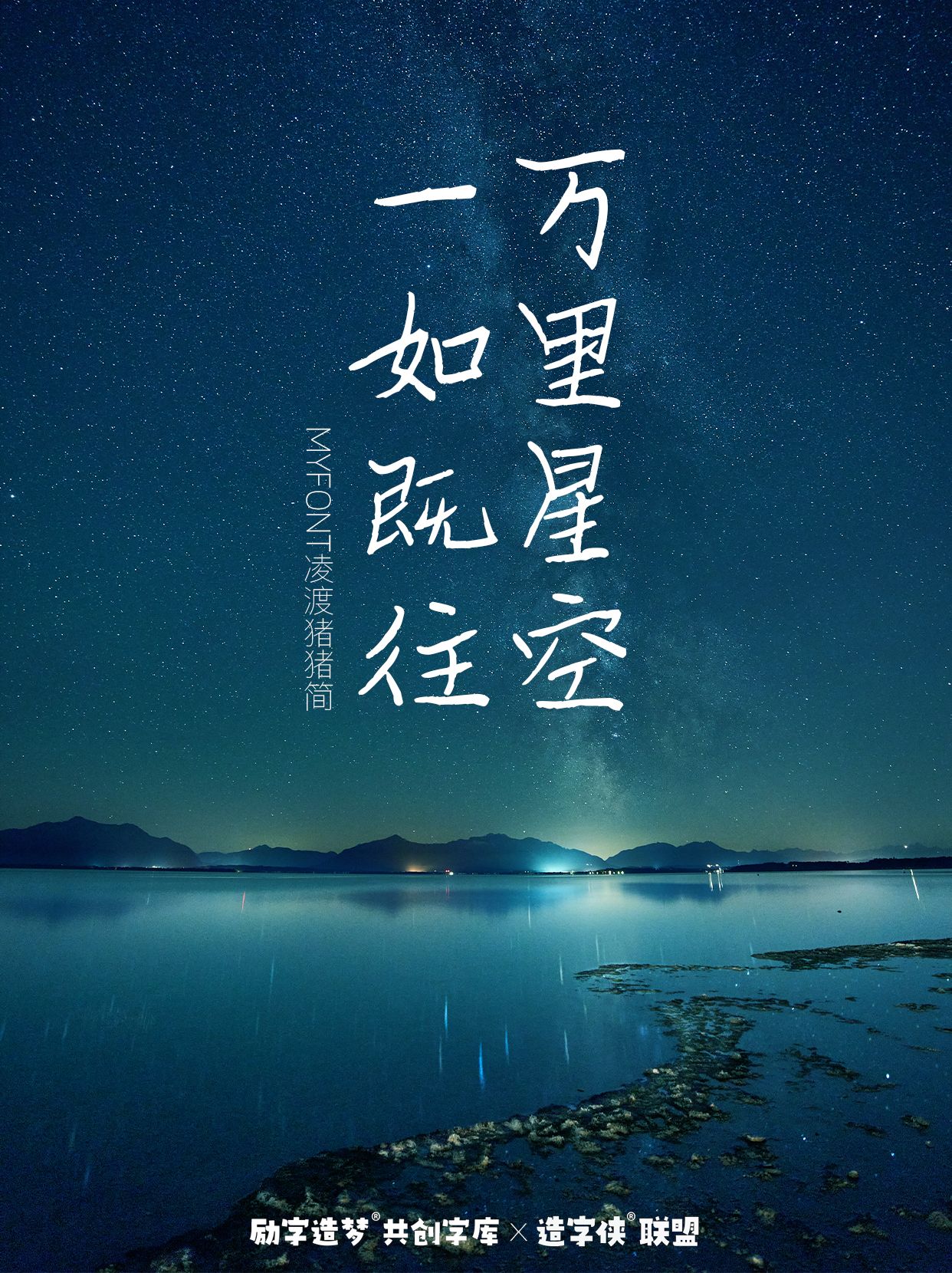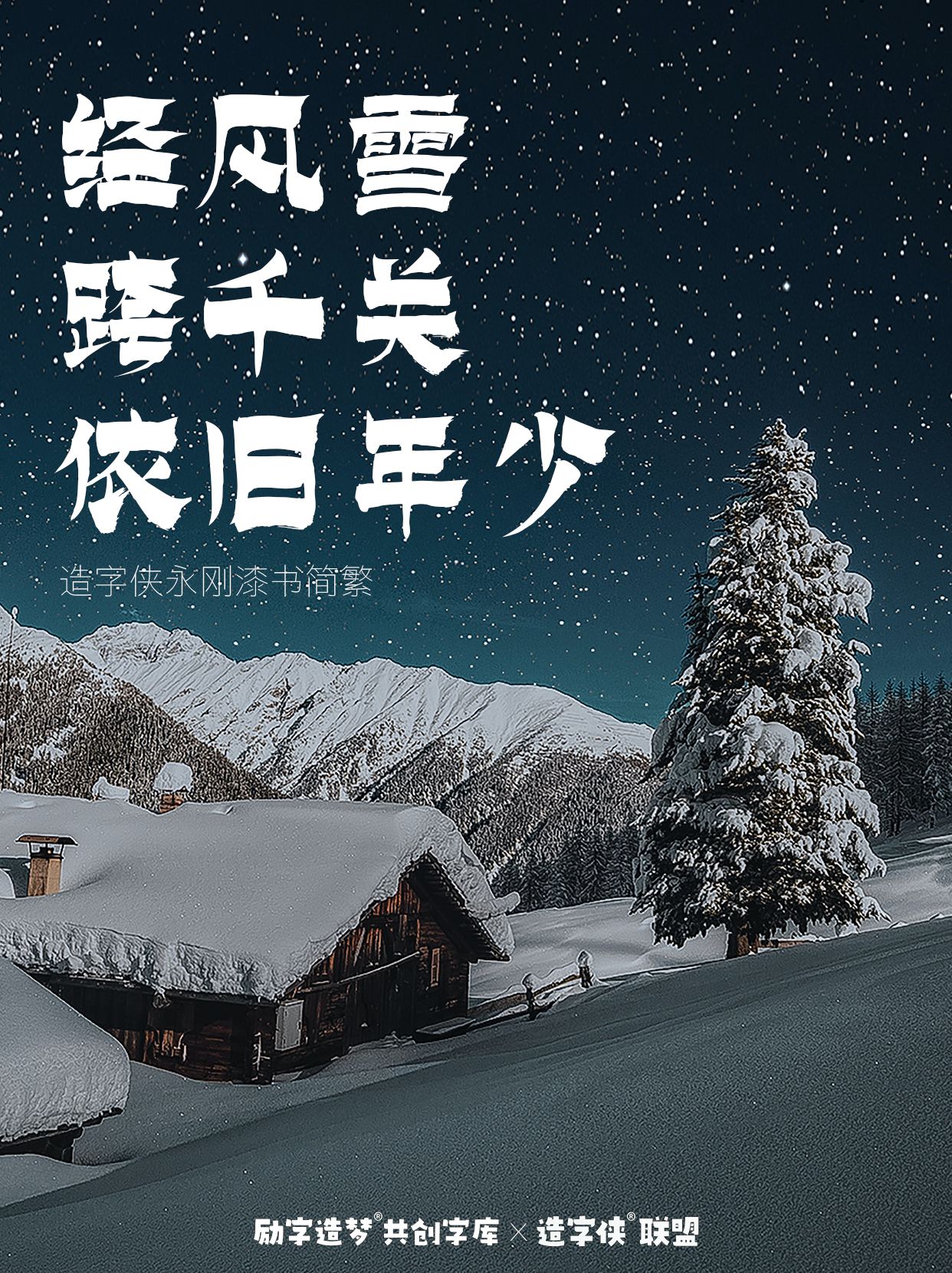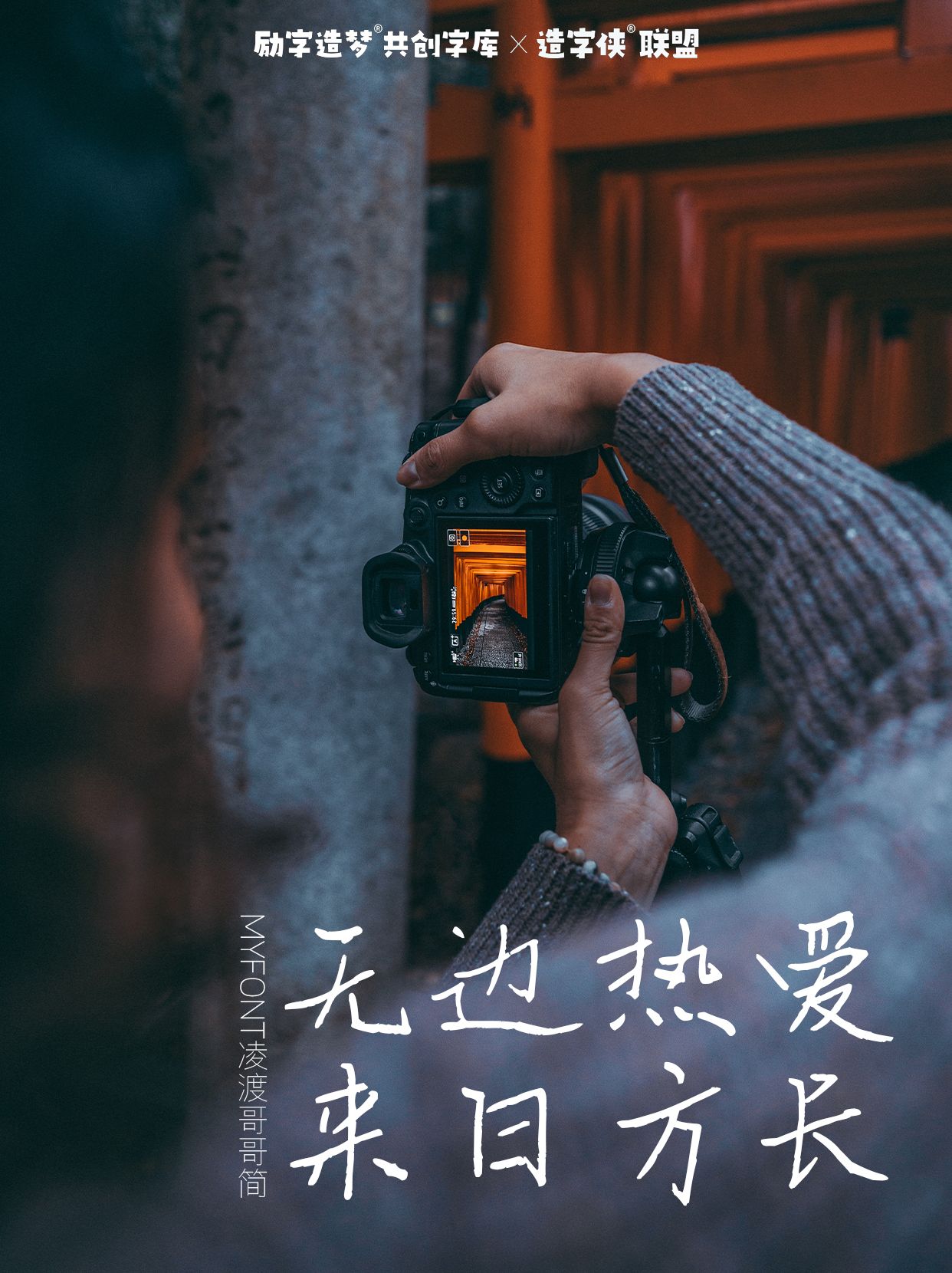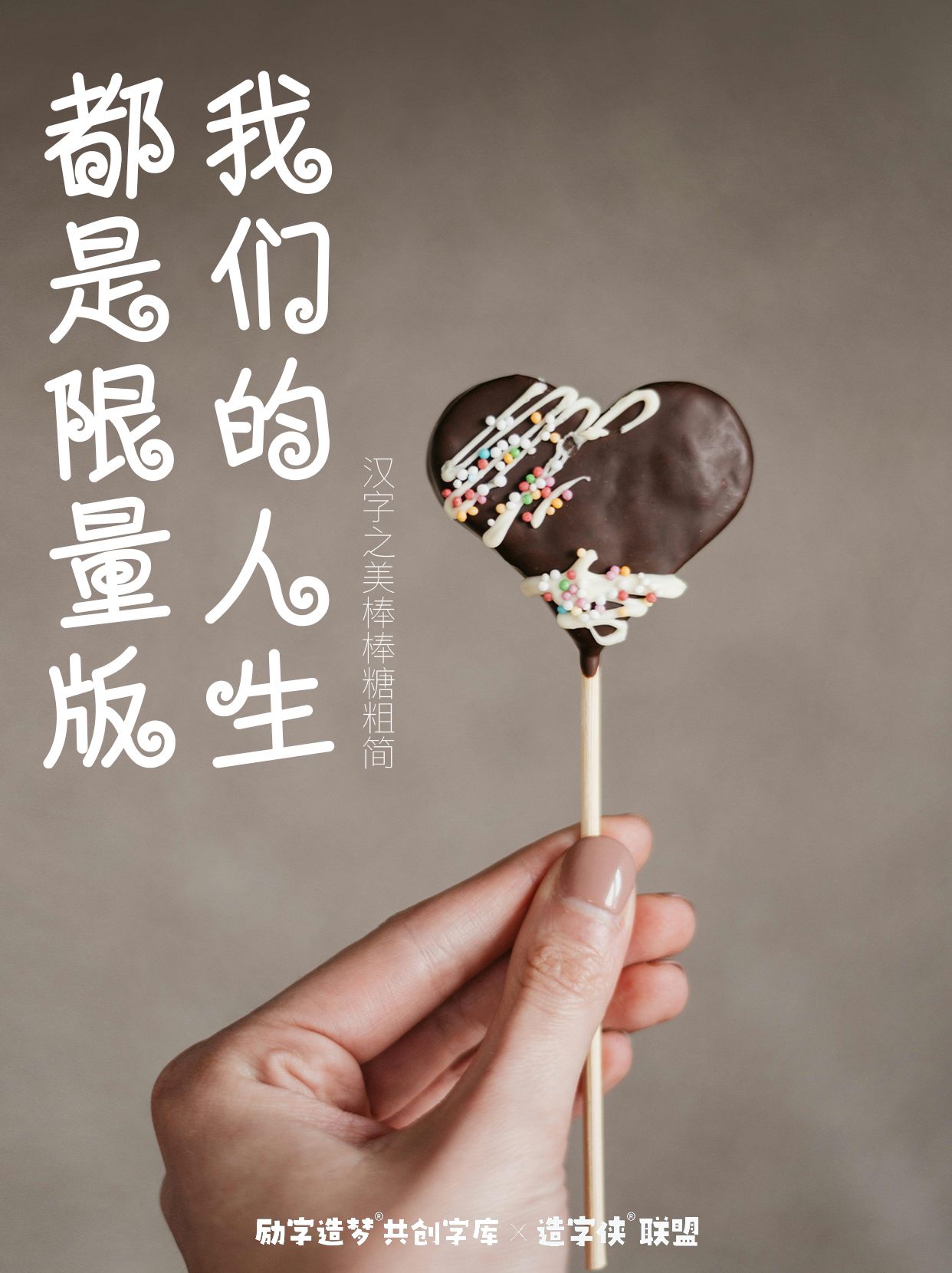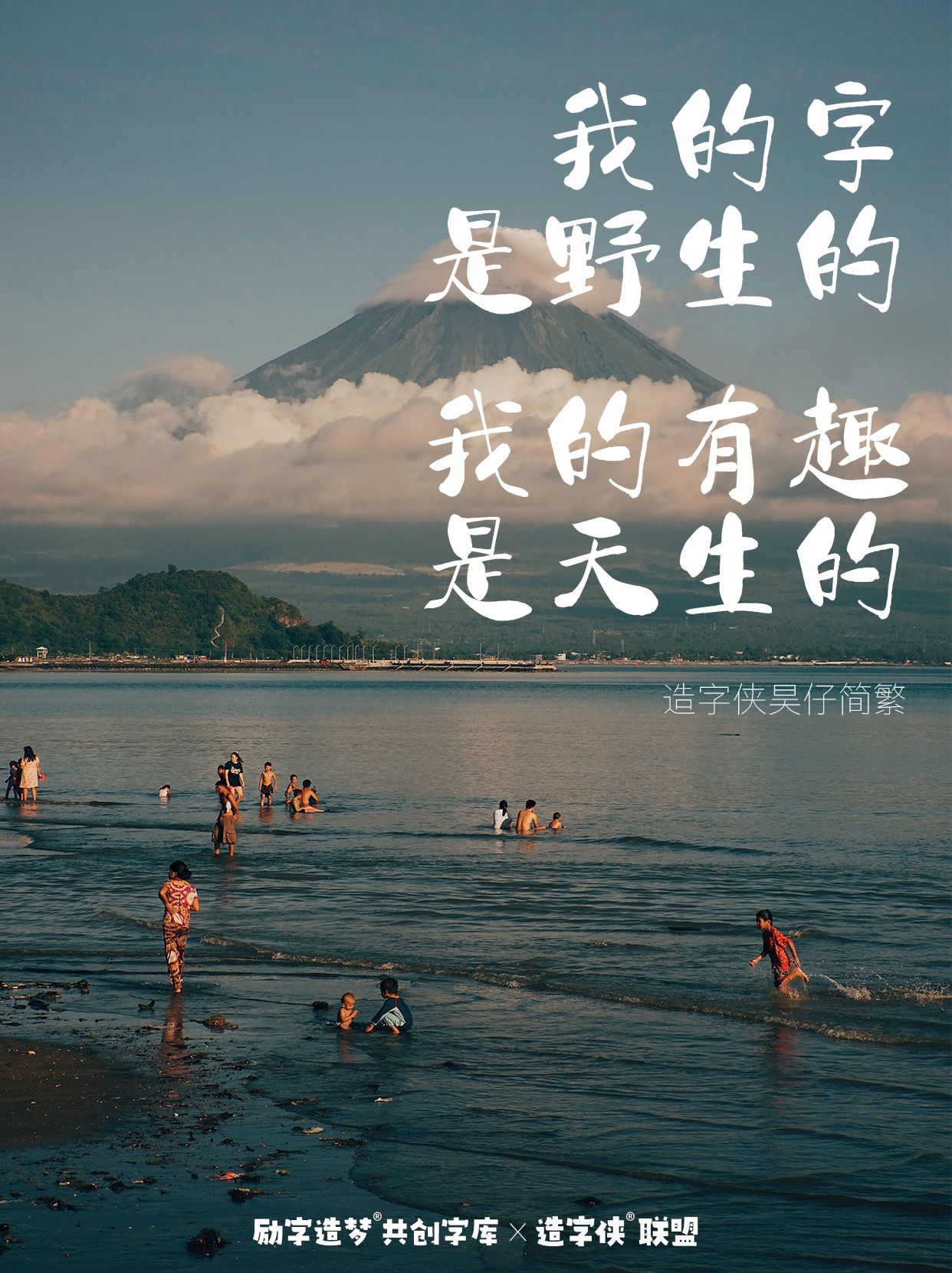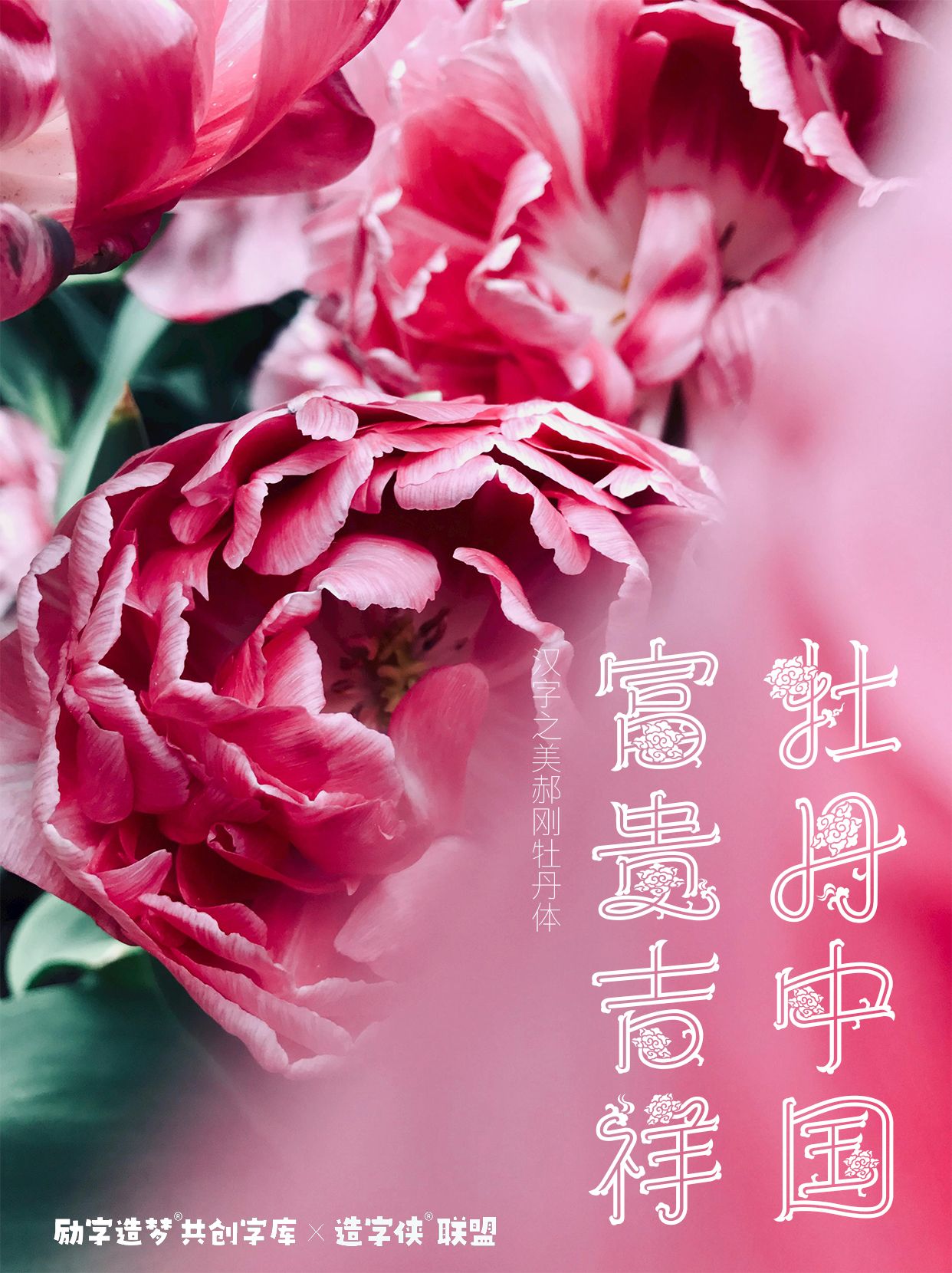
励字造梦共创字库签约字节跳动,首批签约设计师作品惊艳亮相剪映、醒图!
近日,励字造梦共创字库宣布与字节跳动达成战略合作,现首批签约的字体设计师作品已经成功上线剪映、醒图及其海外版CapCut、Hypic中。
励字造梦共创字库与醒图、剪映这两款字节跳动旗下的热门APP,将以这次合作为依托,携手推动共创字体设计在数字内容创作领域的创新应用。
剪映部分签约字体展示
而双方的合作将结合励字造梦字库优秀的字体资源和剪映、醒图的技术实力,共同推动视觉设计领域的发展。
这一合作标志着励字造梦共创字库携首批签约设计师作品,正式进入字节跳动旗下热门产品剪映和醒图的字体生态,为广大创作者提供更加丰富和个性化的字体选择。
这次,通过与字节跳动的合作,更是验证了将进一步拓宽字体设计师多元的展示渠道这一项服务,让更多人了解和欣赏到这些独特的字体作品的同时,也为设计师们提供了一个与业界顶尖企业合作的机会,有助于提升作品的知名度和影响力。
而这些签约作品风格各异,既有简约现代的线条,也有充满个性的国风字体,无一不展现了设计师们的独特创意和精湛技艺。这些字体不仅丰富了平台的视觉呈现,也为用户带来了更加个性化的使用体验。
-签约字体-
MyFont凌渡猪猪简
MyFont凌渡哥哥简
-签约字体-
造字侠永刚漆书简繁
-签约字体-
汉字之美玉龙简
汉字之美郝刚牡丹简
汉字之美棒棒糖粗简
-签约字体-
造字侠昊仔简繁